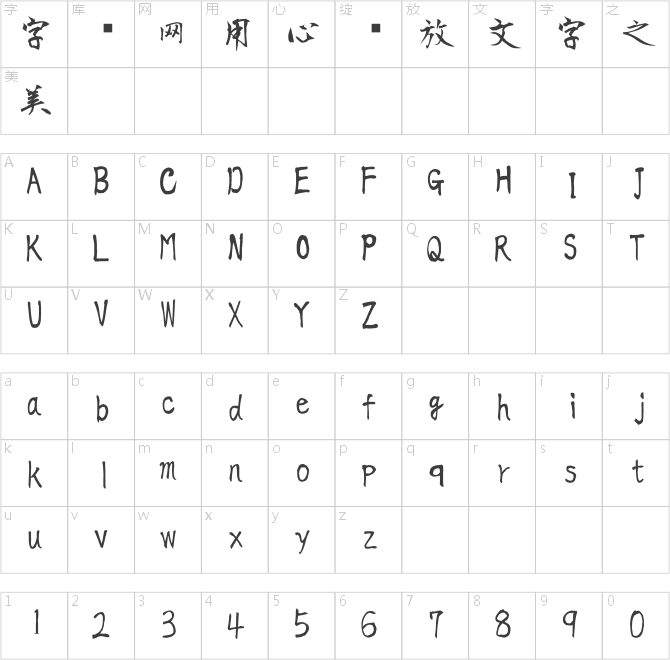
正風(fēng)毛筆字體是中國臺(tái)灣的設(shè)計(jì)師Max基于衡山毛筆行書進(jìn)行字符增補(bǔ)的一款毛筆字體。衡山毛筆行書字體是來自于日本書法家青柳衡山,修改前文字加符號(hào)數(shù)共7,582字,修改后文字加符號(hào)數(shù)共23,699字。第一階段的補(bǔ)字已補(bǔ)齊臺(tái)灣教育部列出的4,808個(gè)常用字,還是有些日常生活的常用字沒有補(bǔ)到。
相較于正風(fēng)毛筆字體的師兄莫大毛筆體,正風(fēng)在個(gè)性上就隨性很多,也造成有部份的一些字很粗,而有些字極細(xì)。原作者的“木”、“米”、“禾”系列常常會(huì)少一撇,是正常的,第一次看到會(huì)覺得有點(diǎn)怪,但是看久就會(huì)習(xí)慣了。
由于是正風(fēng)毛筆字體并非原作者的補(bǔ)字,新加入的字在風(fēng)格上,雖然力求一致,但是難免會(huì)與原作者會(huì)有一些不同。有很多很多字補(bǔ)的“超級(jí)丑”的,幾乎大部份的字都有改善空間,如果有好心人有重做那些丑到爆(或長像怪怪)的字,可以E-mail發(fā)給Max,感謝。
正風(fēng)毛筆字體包含了5個(gè)字重。原本的衡山毛筆行書字體放在Regular字重里,通過程序自動(dòng)產(chǎn)生ExtraLight、Light、Medium、Bold等新的字重。Light字重是把原本的衡山毛筆行書微微調(diào)細(xì)一點(diǎn)點(diǎn)。在ExtraLight的字重裡,可能會(huì)因?yàn)楣P劃太細(xì)造成某些筆畫消失。在Medium和Bold的字重里,可能會(huì)因?yàn)楣P劃太粗造成某些筆畫重疊難以識(shí)別,有粗體字的需求,可以先嘗試使用Bold字重看看,如果發(fā)現(xiàn)效果不如預(yù)期,再改用Medium字重。不能確定自動(dòng)產(chǎn)生出來的字重里每一個(gè)都是完整的字,畢竟程序誤判是常有的事情,所以不是在Regular字重里的筆劃可能會(huì)消失。
本字體是基于改造書法家青柳衡山先生所開發(fā)、發(fā)表的“衡山毛筆フォント行書”字體增補(bǔ)而成。